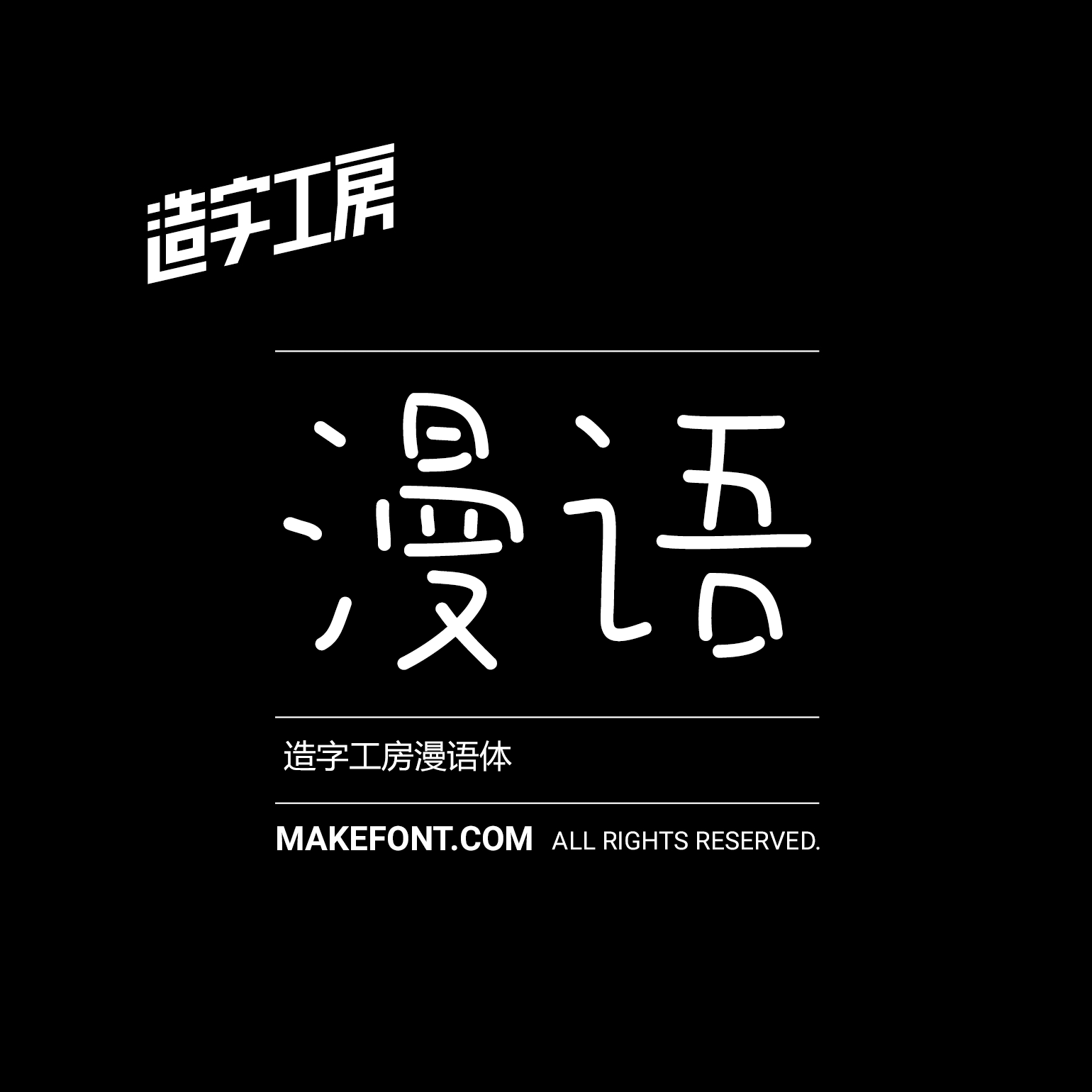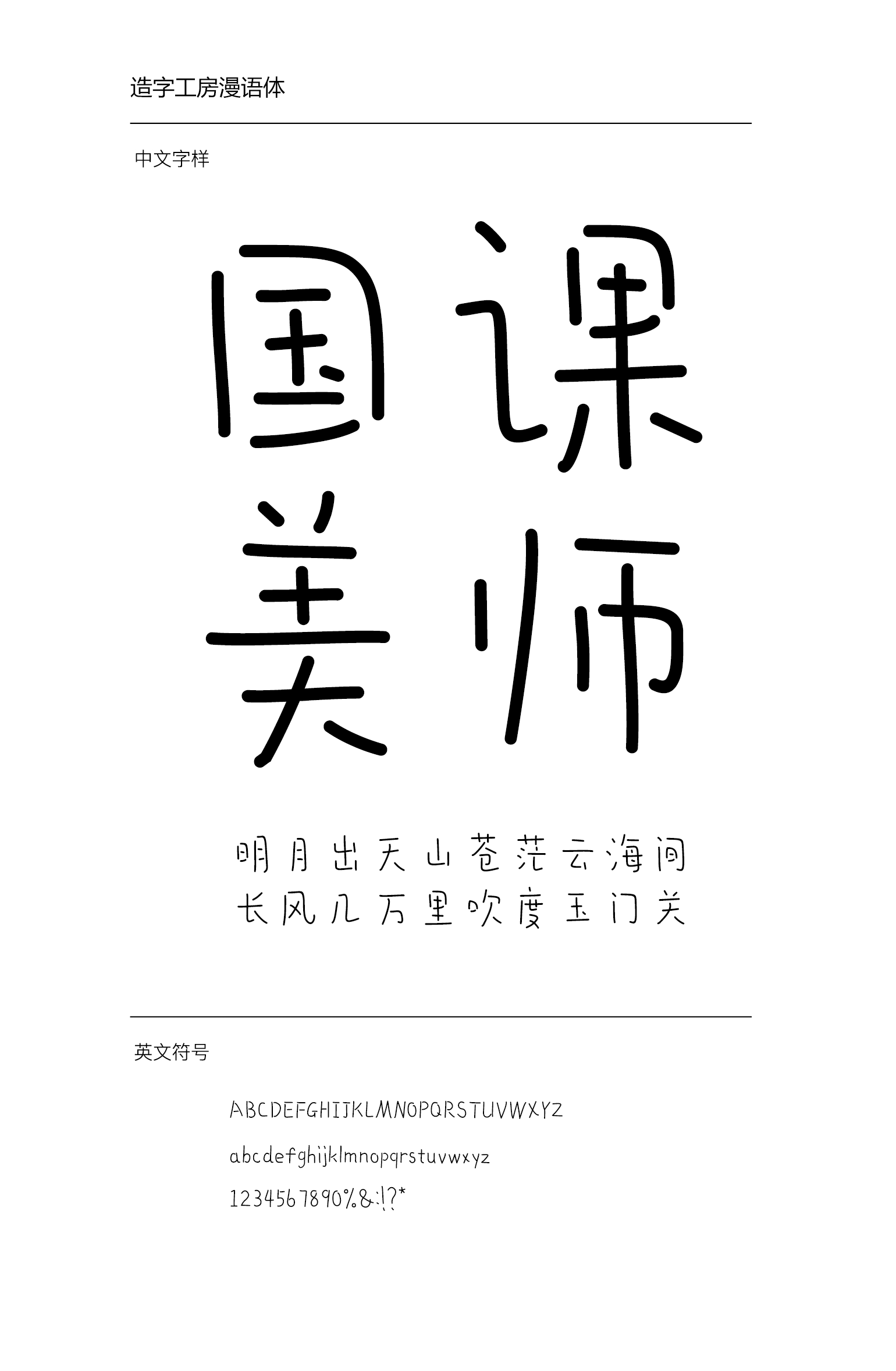
造字工房漫语常规体造字工房漫语体 / MFManYu_Noncommercial-Regular.ttf构自然洒脱,字形活泼、可爱,造型生动有趣,具有灵活的适用性。此款字体适用于儿童读物、报刊杂志标题、广告设计等视觉环境,有着极强的应用空间。本字体为简体字库,采用OpenType/CID格式,Adobe-GB1-5编码。基于中华人民共和国GB2312-80字符集标准,另按需添加101个汉字。共收容字数6864CJK汉字,ASCII常用字符100个。 下载地址百度网盘:https://pan.baidu.com/s/1xQNoDUuVcVa-tMcSA2n-ng 发布日期 2019年11月17日 发布于 书法字体 上篇文章: 汉仪晓波敦黑 下篇文章: 汉仪柏青体简 发表回复 取消回复要发表评论,您必须先登录。